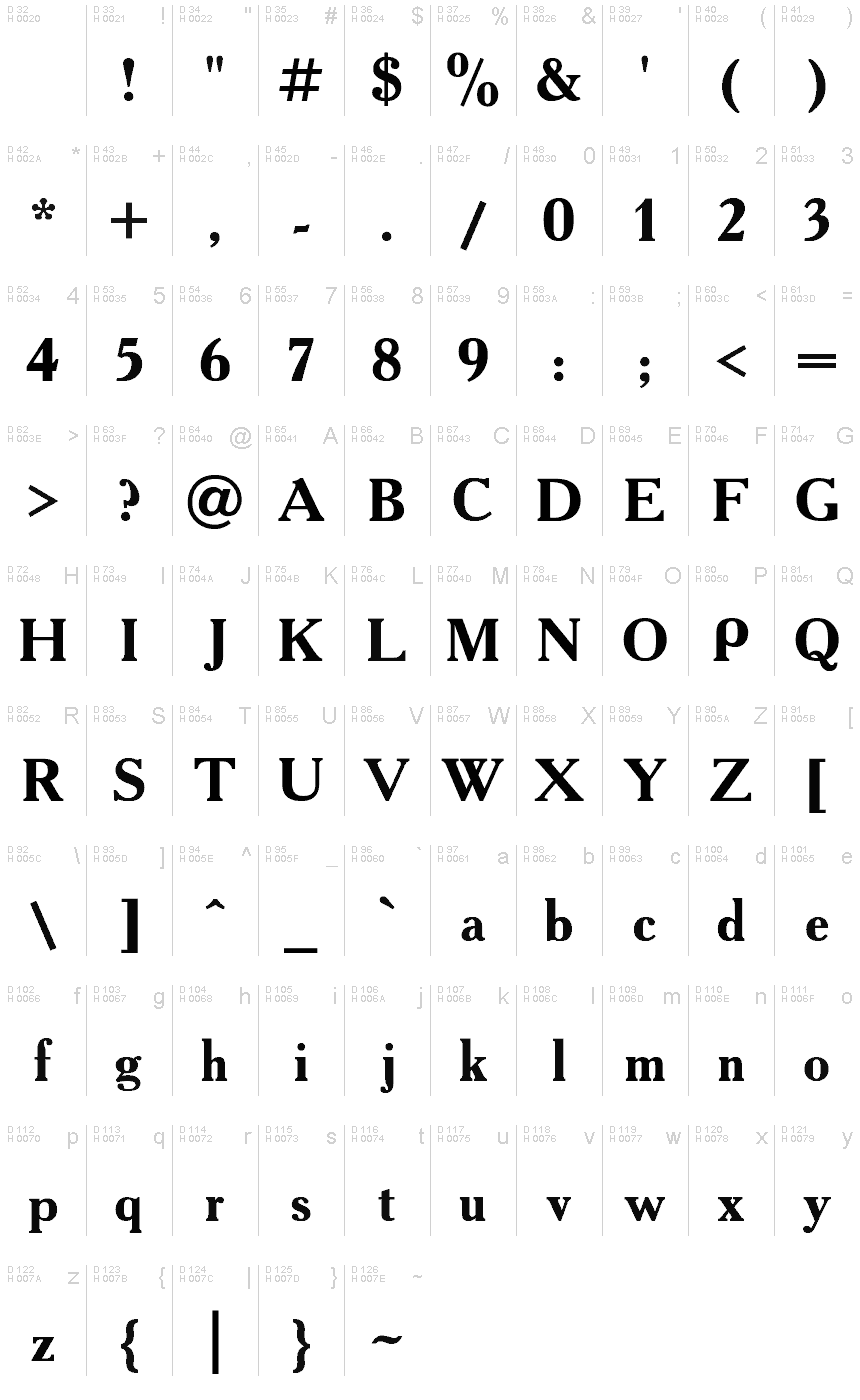
Akademitscheskaya
Die Verfasserversion der berühmten «Akademitscheskaya» Berthold-Garnitur 1910, mit Ergänzungen, außer den Buchstaben der traditionellen russischen Orthografie, deutscher Umlaute & des «sz» («ß»), die für ine vollwertige Förderung der deutschen Sprache notwendig sind, sowie des neu eingeführten russischen Rubelzeichens «₽».